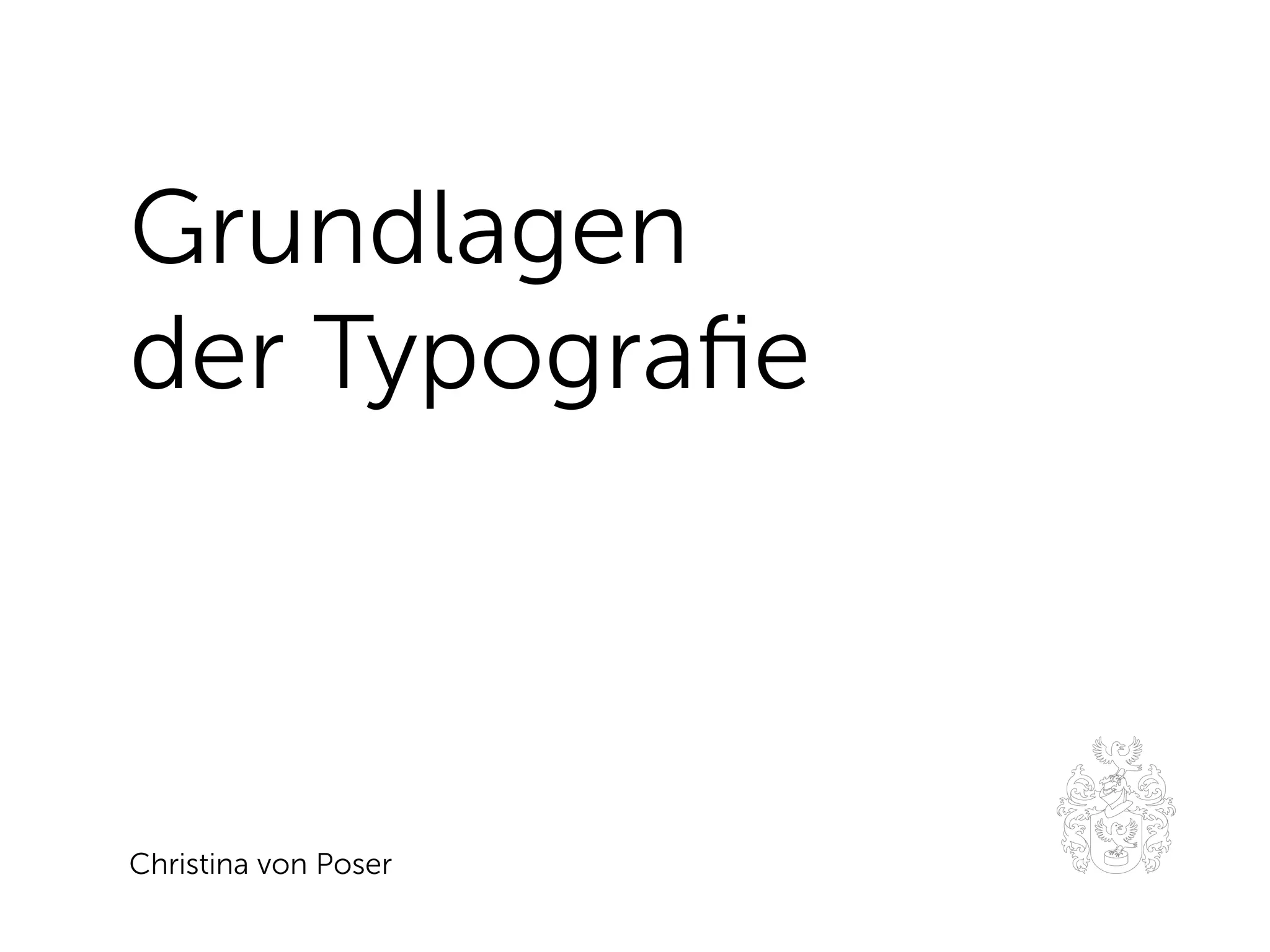
Grundlagen
der Typografie
Zeichensetzung
Die gezeigten Beispiele stellen Regeln für den korrekten typografischen Satz dar.
In einzelnen Fällen kann es dabei jedoch zu Abweichungen zur DIN 5008 kommen.
Weit hinten, hinter den Wortbergen, fern des
Landes Vokalien-Konsonantien leben die Blind-
texte in Buchstabhausen.
2- bis 3-mal
eine 20-Jährige
60-prozentig
Bindestrich, Trennstrich
Maria kochte – wie so o – Reisbrei.
 Alt -
Gedankenstrich                         Alt 0150
München — Stuttgart
Bonn — Berlin
 Shift Alt -
Streckenstrich           Alt 0151
Montag–Samstag
13:00–18:00 Uhr
3–6 Jahre
2000–2010
 Alt -
Bis-Strich        Alt 0150
– Müller
– Meier
– Schulze
 Alt -
Spiegelstrich   Alt 0150
€ 25,–
25,– Euro
€ 25,-
€ 25,--
€ 25,––
 Alt -
Auslassungsstrich   Alt 0150
–7 °C
–15 Punkte
 Alt -
Minuszeichen   Alt 0150
Steuerrecht 45, 69, 149
– und Körperschasrecht 74, 495–498
–, chinesisches 24
 Alt -
Wiederholungszeichen                  Alt 0150
–25–
Finanzamt
–Kasse–
Michael Müller
Straße
Stadt
 Alt -
Einklammerungsstrich   Alt 0150
Müller/Meier/Schulze
ja und/oder nein
1999/2000
Schrägstrich (Slash)
Druck|buch|sta|be
Maria Müller | Hopfenweg 8 | 12345 Stadt
 Shift 7
Senkrechter Strich                          Alt Gr <
Anführungszeichen
»a«
«a»
Guillemets mit Spitzen nach innen und außen
 Alt Q / Shift Alt Q
Alt 0171 / Alt 0187
„a“
Deutsche Anführungen
 Alt ^ / Alt 2
Alt 0132 / Alt 0147
‚a‘
Einfache Anführungen
 Alt s / Alt #
Alt 0130 / Alt 0145
>>a<<
Falsche Anführungen
>a<
Falsche Anführungen
“a“
Falsche Anführungen
‘a‘
Apostroph
’    Shift Alt #
Alt 0146
Falscher Apostroph
‘
Ich mach mir ‘nen Brot.
Ich mach mir’n Brot.
So ‘nen E-Mail-Einladung
So ’ne E-Mail-Einladung
Apostroph
Manni’s Pomme’s-Treff
Mannis Pommes-Treff
Manni’s Pommes-Treff
Apostroph
,;:
Komma (Beistrich)   Semikolon (Strichpunkt)   Kolon (Doppelpunkt)
...
Drei einzeln gesetzte Punkte
…
Dreipunkt/Ellipse/Auslassungspunkt
 Alt .
Alt 0133
Beispiel … für Auslassungspunkte.
Diese verf… Unterbrechungen!
Das wird eine Überraschung …
 Alt .
Dreipunkt (Auslassungspunkt)        Alt 0133
•·
Maria Müller · Hopfenweg 8 · 12345 Stadt
Maria Müller • Hopfenweg 8 • 12345 Stadt
• großer Mittepunkt als Aufzählungspunkt
• hat von Schri zu Schri verschiedene Größen
Kleiner Mittepunkt   Großer Mittepunkt
 Shift Alt 9             Alt Ü
Mittepunkt                            Alt 0183            Alt 0149
( )
(siehe Abb. 2)
Das ist (meiner Meinung nach) schön.
Runde Klammern
[ ]
Das ist ein (etwas an den Haaren herbeige-
zogenes [= dt. Redensart]) Beispiel.
Max schrieb, dass „es […] toll ist, [dass]
 Alt 5 / Alt 6
Eckige Klammern                              Alt Gr 8 / Alt Gr 9
A|po|s|t|roph der; -s, -e gr.-lat. ; „abgewandt;
abfallend“>: […]
Fehlen im ASCII-Zeichensatz und werden daher
o durch „<“ und „>“ ersetzt.
Spitze Klammern
{ }
}
Müller
Meier           Personen
Hopf
 Alt 8 / Alt 9
Akkoladen (Nasenklammer, geschweifte Klammer)   Alt Gr 7 / Alt Gr 0
0201 12345678
0201 123456-78
+49 201 12345678
+49 201 123456-78
0201 12 34 56 78
0201 1 23 45 67 89
Kontonummer
0123456789
0 123 456 789
Bankleitzahl
123 456 00
Branchentypische
Schriften
Baumschule
Architekten
Schokolade
Parfümerie
Medikamente
Akropolis
Bioladen
DÖNER KEBAP
Copyshop
Sanitärbetrieb
Antiquitäten
Bowling
Opernhaus
Gärtnerei
SPEDITION
THE MOVIE FONT
Abwandlung
bekannter Logos
Literatur
Anatomie der Buchstaben.
Basiswissen für Schriftgestalter.
Lesetypografie
Wegweiser > Schrift.
Erste Hilfe im Umgang mit Schriften.
Was passt, was wirkt, was stört.
Erfreuliche Drucksachen durch
gute Typografie.
Eine Fibel für Jedermann.
Gute Typographie ist so, wie ein guter Diener
gewesen sein mag: da und doch nicht bemerkbar;
unauffällig, aber eine Voraussetzung des
Wohlbefindens, lautlos, geschmeidig […]
Gute Schri, richtige Anordnung; das sind die beiden
Pfeiler aller Schrikunst.
Jan Tschichold